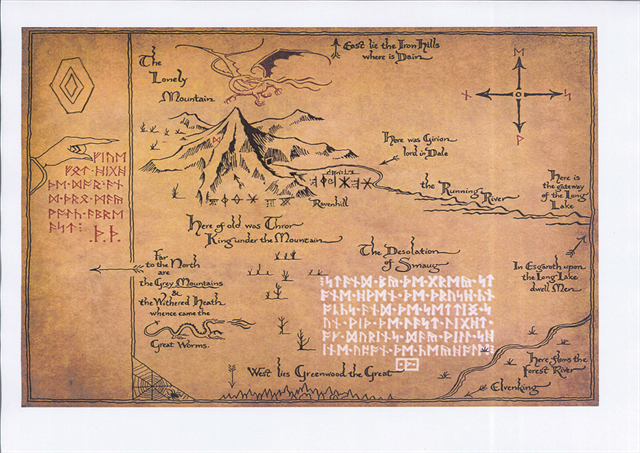
Kann mir jemand sagen, was diese zeichen bedeuten?
Die 2 mal 6 zeichen am berg, nicht das geschriebene.
Es müsste eine zwergenschriftart sein und stammt aus einem quitz. Es müssten zahlen sein.
Aber diese durchgestrichenen karos und spiegelverkehrten "E" konnte ich nirgends finden.?!?
Es geht nicht um den weiss geschriebenen text, sondern um diese 2 x 6 zeichen unten am berg und rechts vom berg.
Diese Zeichen kommen auf den originalen Mittelerde-Karten nicht vor – aus welchem Quiz stammt dein Beispiel und was genau wird gesucht?
Geh mal auf Google-Bildersuche mit folgenden Suchworten
futhark + zahlen
da glaube ich einige gesehen zu haben, die deinem Bild entsprechen.
Es ist aus einem Geocaching Mystery:
Es müssen anhand vom bild gps-koordinaten ermittelt werden.
das bild selber stammt aus "herr der ringe", ist jedoch um diese rätselhaften symbole erweitert worden
den Stern habe ich der Runenschrift auch gefunden, jedoch keine durchgestrichenen karos und spiegelverkehrte "E".
Irgendwann wirds schon noch "klick" machen...